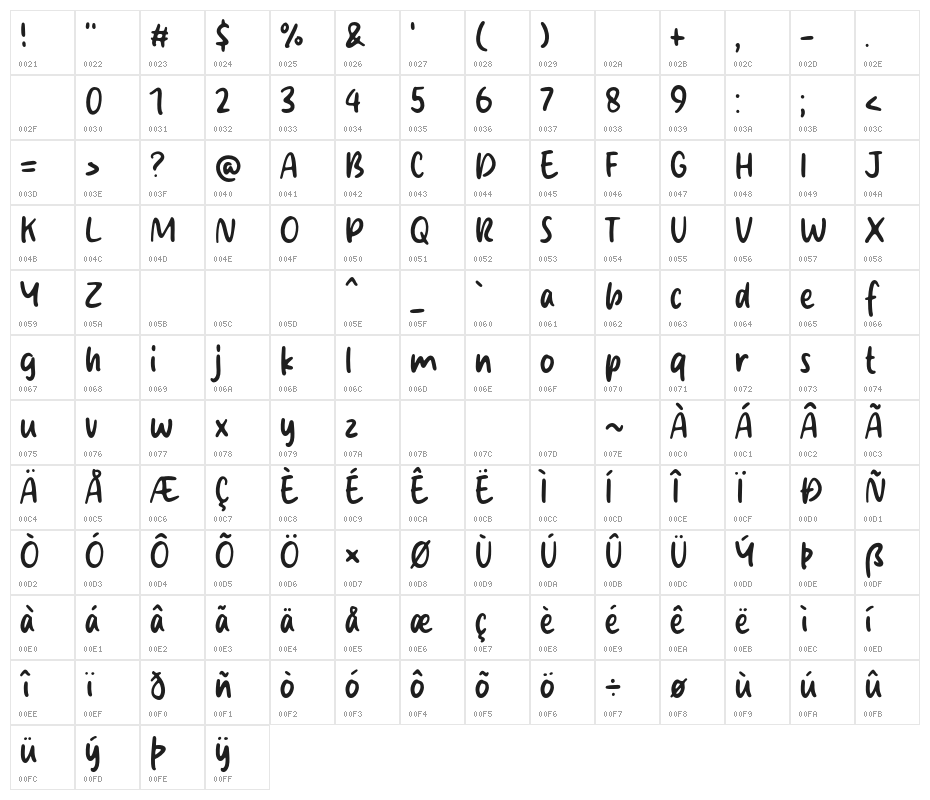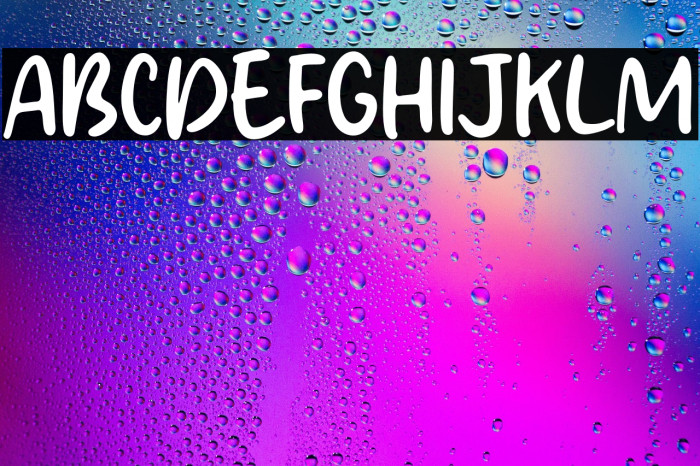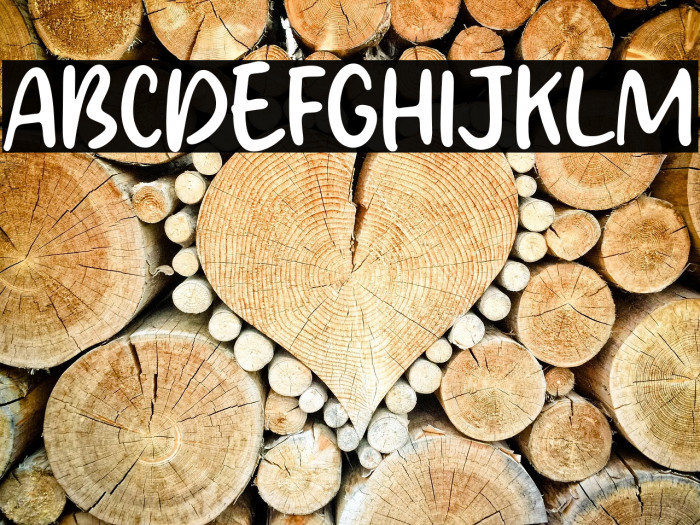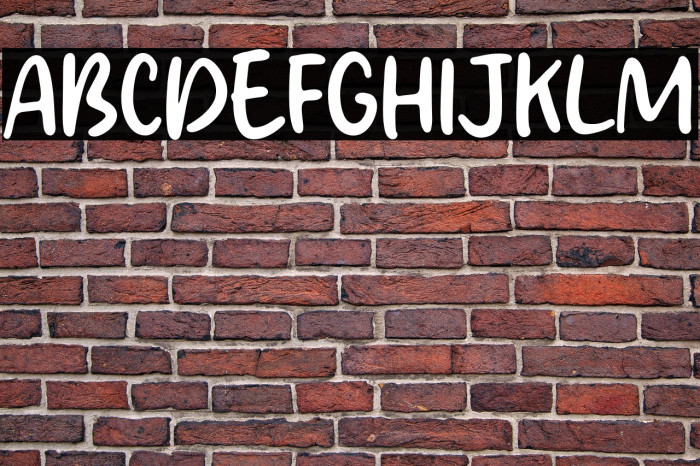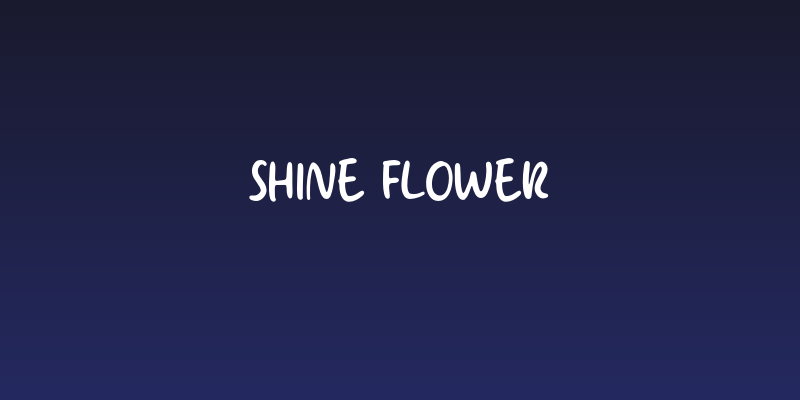
Shine Flower Font
| Stile generale | Playful, Casual |
| Caso d'uso | Headlines, Logos, Informal Text |
| Progetti proposti | Ideal for greeting cards, children's books, playful branding, and social media graphics. |